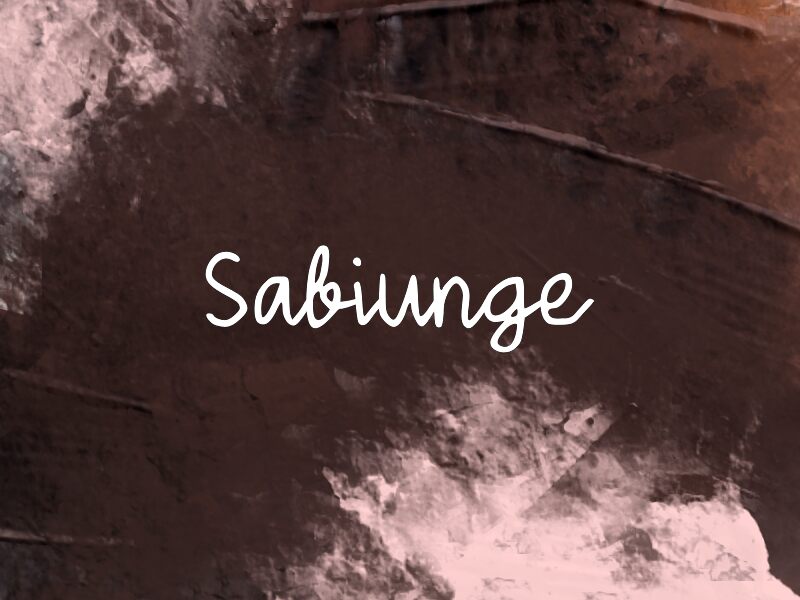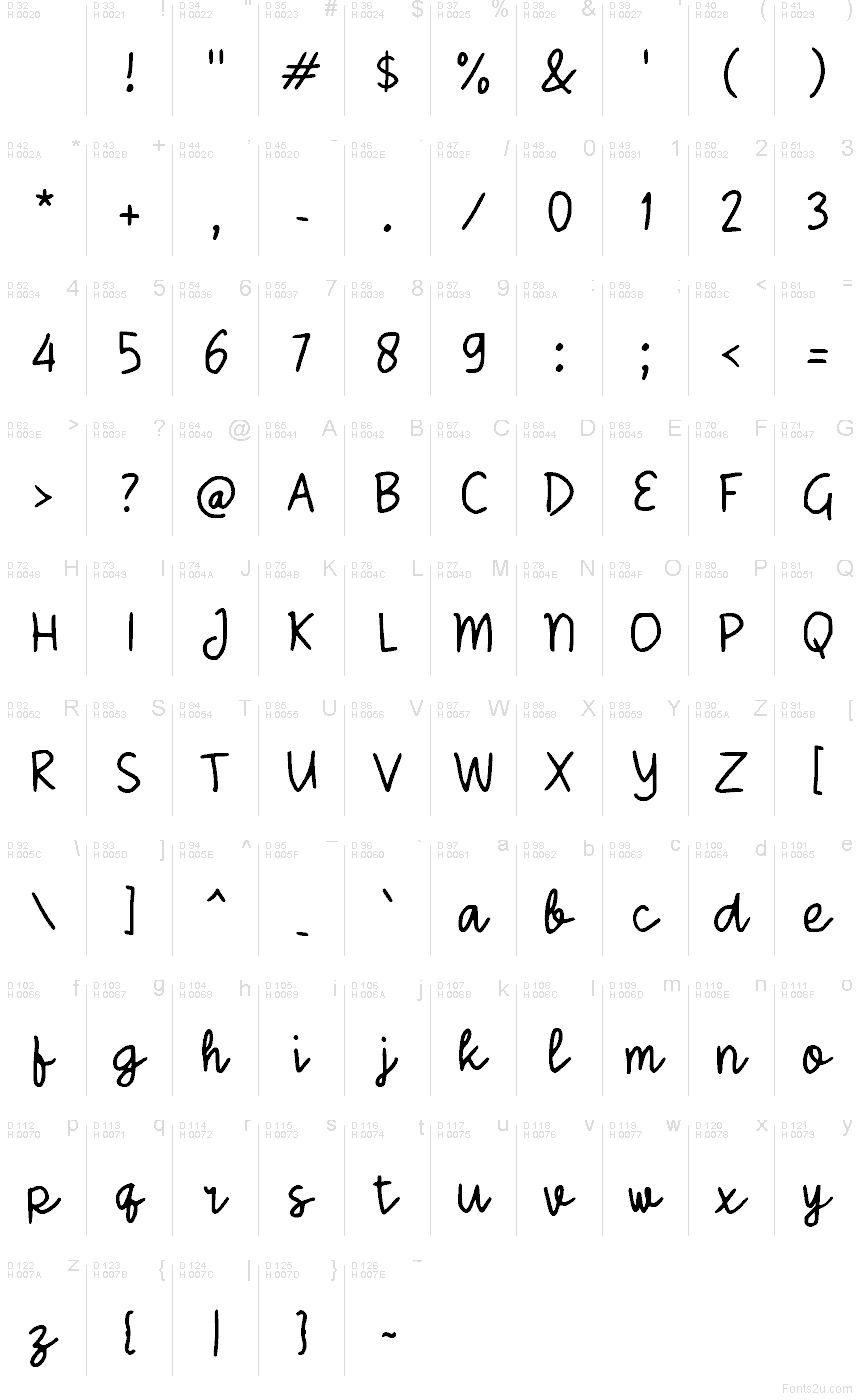
Sabiunge
Sabiunge od Wep je bezplatné ručně psané písmo, které definují dlouhé, lehké křivky a uvolněný rytmus. Působí spíše jako rychlé písmo fixou než jako vycibřená kaligrafie. Zaoblené tahy a vysoké smyčkové tvary dodávají písmu fluiditu a osobitost, zatímco lehce nepravidelný tok zajišťuje, že nepůsobí strojeně.
Tento neformální pohyb využijete v menu kaváren, na obalech, v příspěvcích na sociálních sítích, přáních či jako podpisy značek, kde je lidský dotek důležitější než přísná formálnost. Sabiunge skvěle ukotví i grafiky s citáty nebo záhlaví blogů, zejména pokud hledáte písmo, které působí spontánně a ne příliš připraveně.